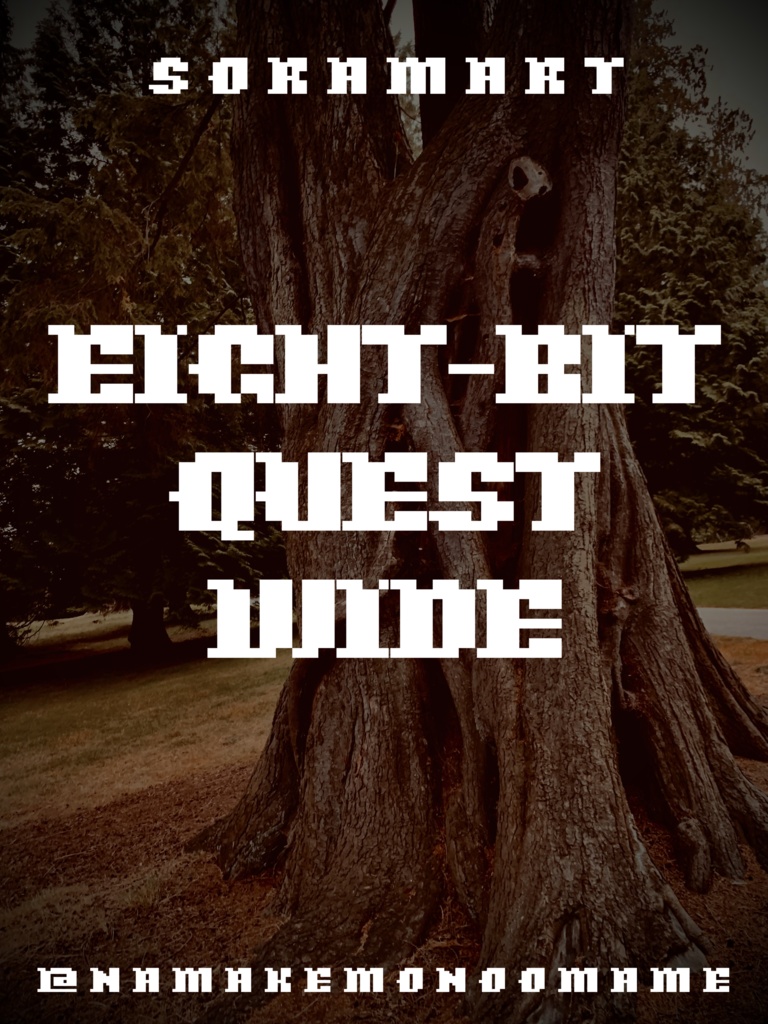
そらマートフォントデータ”Eight-bit Quest Wide”Digital2,500 JPY放入購物車Buy a GiftAbout Giftドット調スタイル+ブラックレターの太文字フォント "Eight-bit Quest Wide" です。 「TrueTypeフォントファイル」という形式です。 ダウンロードした後、Zipファイル内のデータをインストールしてお使いください。 このフォントは商用利用可となっております。 お客様の制作・創作活動のお役に立てれば幸いです。 ※使用上の注意事項などは、添付のReadmeをお読みください。そらマートVisit FANBOX!Fontsフォントデータ”Bubblegum Beat”そらマート0 JPYFontsフォントデータ”Caltrop Serif LLL”そらマート2,500 JPYFontsフォントデータ”Caltrop Serif LL”そらマート0 JPYFontsフォントデータ”Caltrop Serif”そらマート0 JPYFontsフォントデータ”Tonik Crate Super Long”そらマート2,500 JPYFontsフォントデータ”Dot Eat Bug Acid”そらマート2,500 JPYFontsフォントデータ”Dot Eat Bug Mild”そらマート2,500 JPYFontsフォントデータ”Dot Eat Bug”そらマート2,500 JPYFontsフォントデータ”Solid Voltage Strike”そらマート2,500 JPYFontsフォントデータ”Solid Voltage”そらマート2,500 JPYFontsフォントデータ”Henge Edge Rock”そらマート2,500 JPYFontsフォントデータ”Henge Edge Tall”そらマート0 JPYFontsフォントデータ”Henge Edge”そらマート0 JPYFontsフォントデータ”Chisel Stroke Wide”そらマート2,500 JPYFontsフォントデータ”Chisel Stroke”そらマート2,500 JPYFontsフォントデータ”Crushed Can Serif Empty”そらマート2,500 JPYFontsフォントデータ”Crushed Can Serif Wide”そらマート2,500 JPYFontsフォントデータ”Crushed Can Serif”そらマート2,500 JPYFontsフォントデータ”Dolce Cube Tall”そらマート2,500 JPYFontsフォントデータ”Dolce Cube”そらマート2,500 JPY查看更多